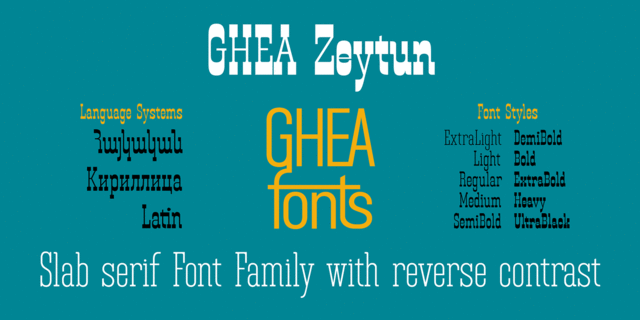
Зейтун – узкий брусковый шрифт с необычным ассортиментом начертаний. Его десять начертаний от Extra Light до Black изменяются по насыщенности за счет расширения брусковой засечки, что создает диапазон от неконтрастного до сильного обратного контраста. Разный вес засечки вызывает разные ассоциации, от современного хипстерского гастропаба, через классический вестерн и вплоть до ироничной пародии на вестерн. Шрифт разработал Эдик Габузян в 2018 году.
Ассоциации c начертанием GHEA Zeytun Semi BoldКачества и характер:
ковбойский, старомодный, ремесленный, гангстерский, исторический, блатной, фермерский, крафтовый, пивной, бандитский, самобытный, оригинальный, интересный, характерный, гибкий, стальной, остроумный, четкий, западный, громкий, деревянный, устойчивый, статичный, винтажный, резкий, экстравагантный, олдскульный, кинематографичный
джинсы, конюшня, охота, оружие, кино, вестерн, салун, виски, алкоголь, сигары, ресторан, туризм, упряжка, седло, ферма, телега, шериф, ранчо, трактир, родео, лошадь, бык, ремесло, кузнец, мясо, детектив, кузница, револьвер, ковбой, цирк, обед, ужин, казино, пиво, карты, лавка, базар, игра, ярмарка, аттракцион, табак, ломбард, мафия, одежда, бар, техника, инструмент, машина, железная дорога, паровоз Стилистика: